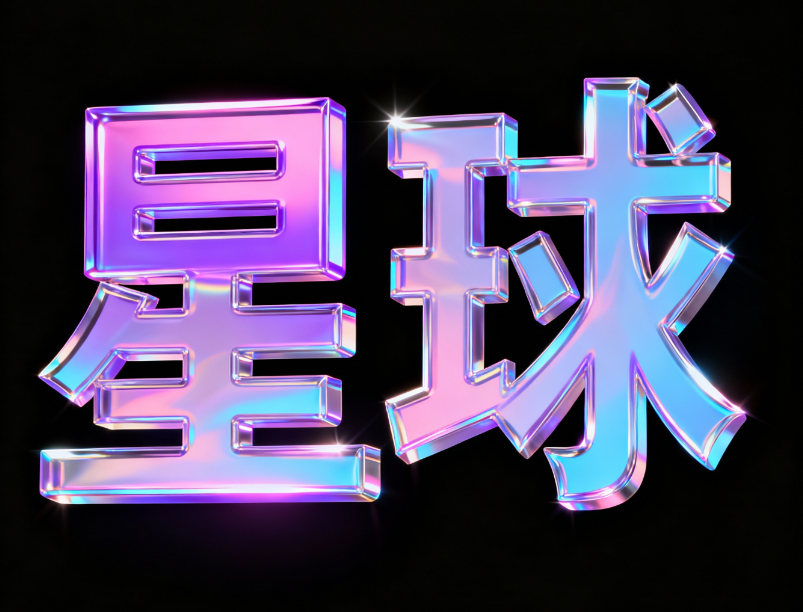
艺术字体设计,文字内容 “星球”,采用 3D 立体全...
艺术字体设计,文字内容 “星球”,采用 3D 立体全...AI字体提示词
风格定位
适合做风格探索与字形灵感延展。
适合场景
海报设计、品牌标题、电商设计、创意视觉
艺术字体设计,文字内容 “星球”,采用 3D 立体全息渐变风格,色彩呈现粉紫到淡蓝的梦幻渐变,字体表面带有强烈的金属光泽与透明质感,如霓虹般炫彩夺目。字体具备明显的立体厚度,边缘锐利且带有高光反射。背整体风格充满未来科技感,炫酷吸睛,强调字体立体层次与全息色彩的流畅过渡,黑色背景
可替换关键词
金属纸张肌理浮雕高对比立体阴影强笔触艺术字体设计文字内容“星球”采用
生成建议
• 先保留核心风格词,再替换材质、颜色和光影词做多轮尝试。
• 如果用于品牌标题字,补充品牌气质、行业属性和情绪关键词。
• 如果用于海报或电商标题,额外强调大字、对比度和视觉冲击力。